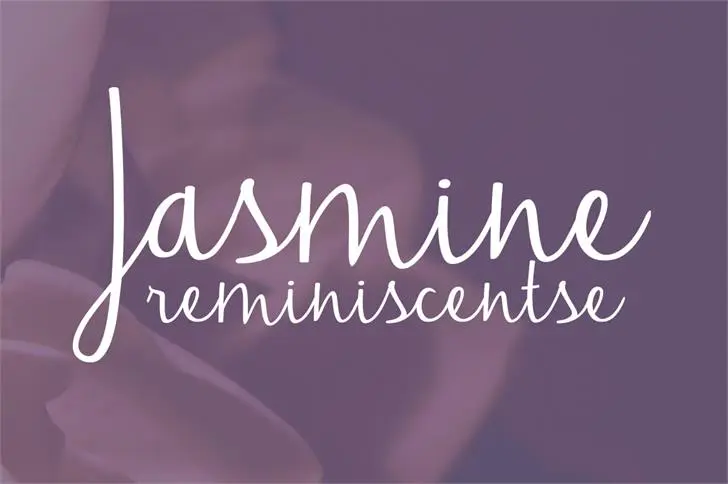
Jasmine Reminiscentes é uma fonte script perfeita para criações que transmitem sutileza e elegância. Desenvolvida pelo designer Hamilton, esta fonte é ideal para aplicativos comerciais, oferecendo um toque de sofisticação em qualquer projeto gráfico. Com suas linhas fluidas e detalhes cuidadosamente moldados, Jasmine Reminiscentes é perfeita para descrições pessoais, parágrafos de texto e até mesmo logos profissionais. Com sua capacidade de criar texturas suaves e movidas pelo tempo, esta fonte oferece uma maneira criativa de incorporar elementos gráficos em seus designs. Suas curvas românticas e nuances sutis garantem que seu design seja encantador e memorável, tornando-a uma escolha ótima para qualquer designer buscando imprimir um toque único e sofisticado nos trabalhos finais. Visite a página dos downloads do designer Hamilton para explorar mais detalhes sobre Jasmine Reminiscentes.